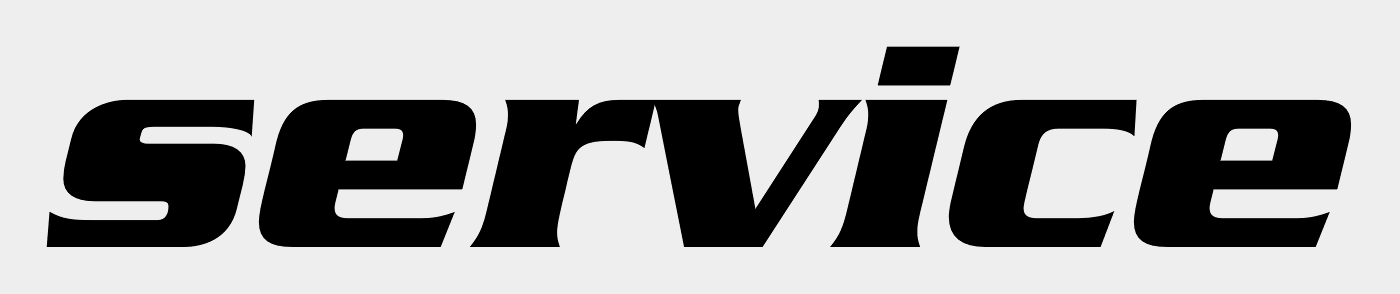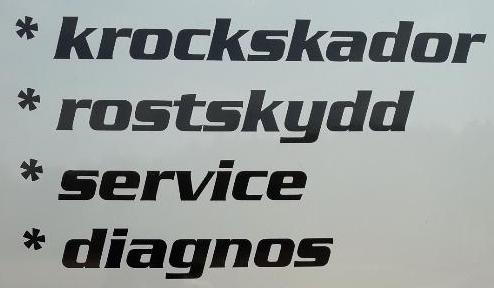
kleine Autowerkstatt nutzt Julius Black - italic - oder?
Ein existierendes Schild einer kleinen värmlandischen Autowerkstatt soll überarbeitet werden.
Julius Black habe ich installiert - aber nicht die Kursiv-Version. Warum kann ich diese nirgends finden ??
Du hast versehentlich die "Serif" erwischt … die "Standard" hat das hohe s.